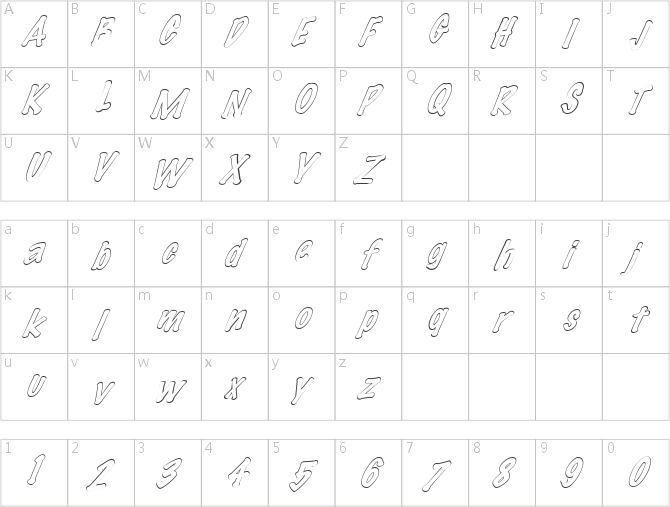
FZ HAND 14 HOLLOW ITALIC 詳情頁
FZ HAND 14 HOLLOW ITALIC字體字庫是一款讓人賞心悅目、百看不厭的英文字體,適合各類廣告和產(chǎn)品包裝設(shè)計(jì)應(yīng)用,字體大小0.1MB,格式為ttf字體,上傳用戶是星期一,作者/版權(quán)方為未知